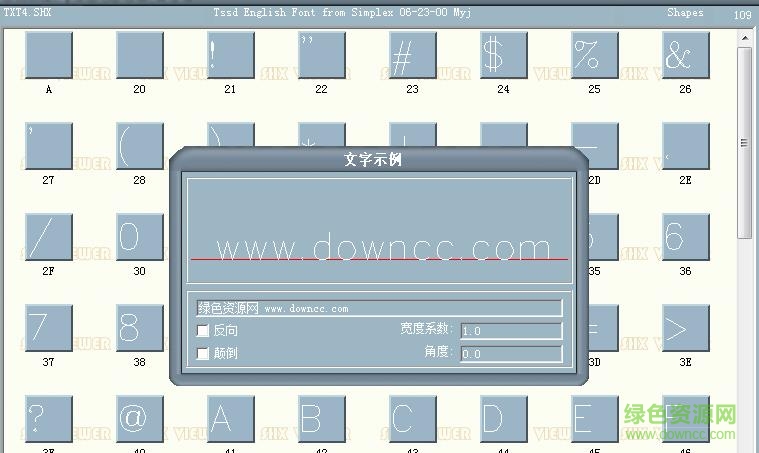
txt4.shx是cad字體,不同于一般的字體文件,這款字體提供的作用在于能夠進行特定的字符輸入,讓你在相關(guān)的制圖過程中快速調(diào)用!
1、這種字型的優(yōu)點是在顯示時字符可以任意縮小放大,缺點是需要做大量的處理。
2、這款字體清晰明了,十分整潔美觀,在字體結(jié)構(gòu)上最求完美帶給你不錯的視覺體驗